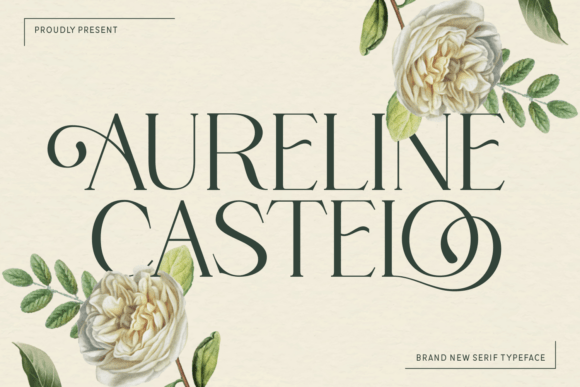
Aureline Castelo - Elegant Serif Typeface
Die richtigen Designelemente zu finden, kann eine Herausforderung sein, aber Aureline Castelo - Elegant Serif Typeface bietet eine außergewöhnliche Sammlung, die Ihre Arbeit sofort aufwertet.
Egal, ob Sie POD-Produkte (Print on Demand), Hochzeitseinladungen oder Social-Media-Grafiken erstellen, Aureline Castelo - Elegant Serif Typeface ist die ideale Wahl.